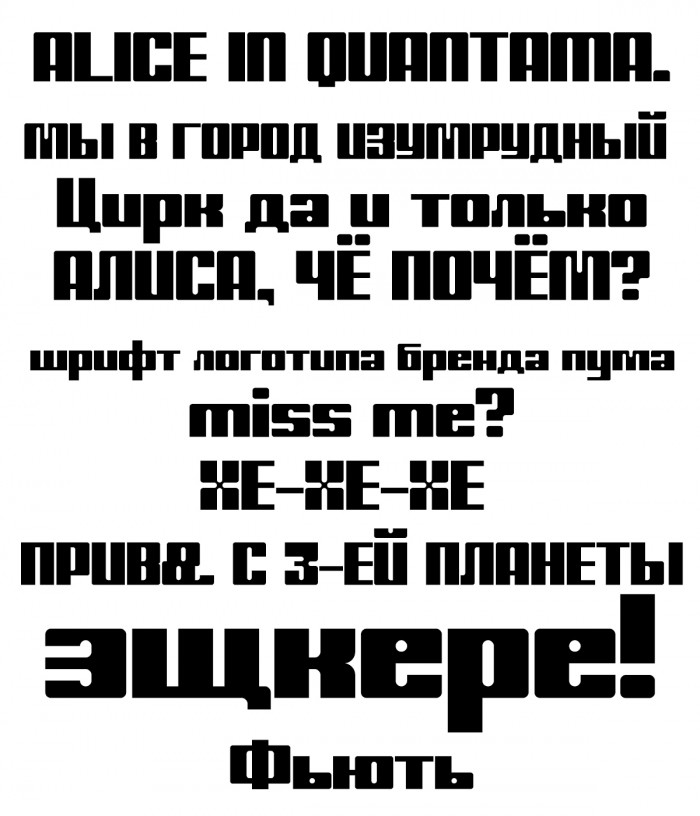
• Брутальный шрифт, полностью забивающий собой строку, который при этом старается взять в себя боьше воздуха, свободы и дерзости, как в строчной x, что хорошо подходит уличному стилю. Стиль довольно консервативен, отсылает при этом к ещё модным сейчас 70-ым.
nice remake but as i believe the Cyrillic letters are designed by you tho